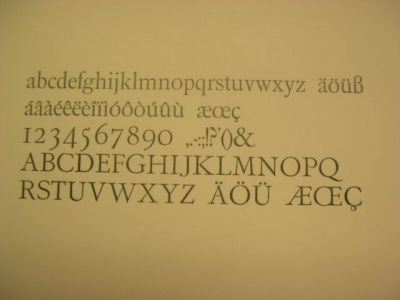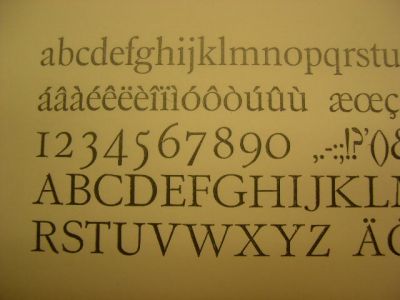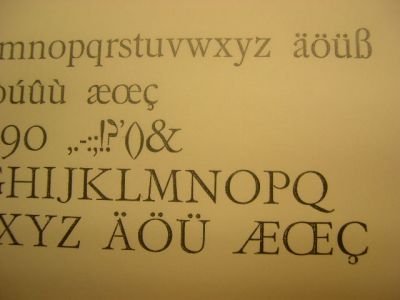
Wer kennt den Namen dieser Antiqua?
Ich habe hier zwei Kästen mit einer wunderschönen Antiqua. Sie dürfte aus der Zeit nach 1926 sein (steht nicht im Seemann-Handbuch). Ihr Name (auf den Kästen) lautet: Neuzeit.
Ein Bleisatz-Freund vermutet Heinrich Hoffmeister (1910) als Entwerfer.
Und es gibt wohl noch einen anderen Eintrag:
Schriftgießerei Wagner & Schmidt und als Schriftschöpfer wird
Otto Tech angegeben.
Klassifiziert ist die Schrift jedoch erst, wenn alle Informationen vorhanden sind:
Name
Schriftgießerei
Erstguß-Jahr
Entwurf
Also bitte ich um Eure Hilfe.
Dies schrieb mir ein Bleisatz-Freund:
"bei der Antiqua Klassifizierung vom 14. 6. handelt es sich um die Französische Elzevir Antiqua.
Sie wurde 1891 von Genzsch & Heyse von der Pariser Firma Deberny & Cie erworben. Es wurden noch größere Grade und Titelversalien dazu geschaffen durch G&H."